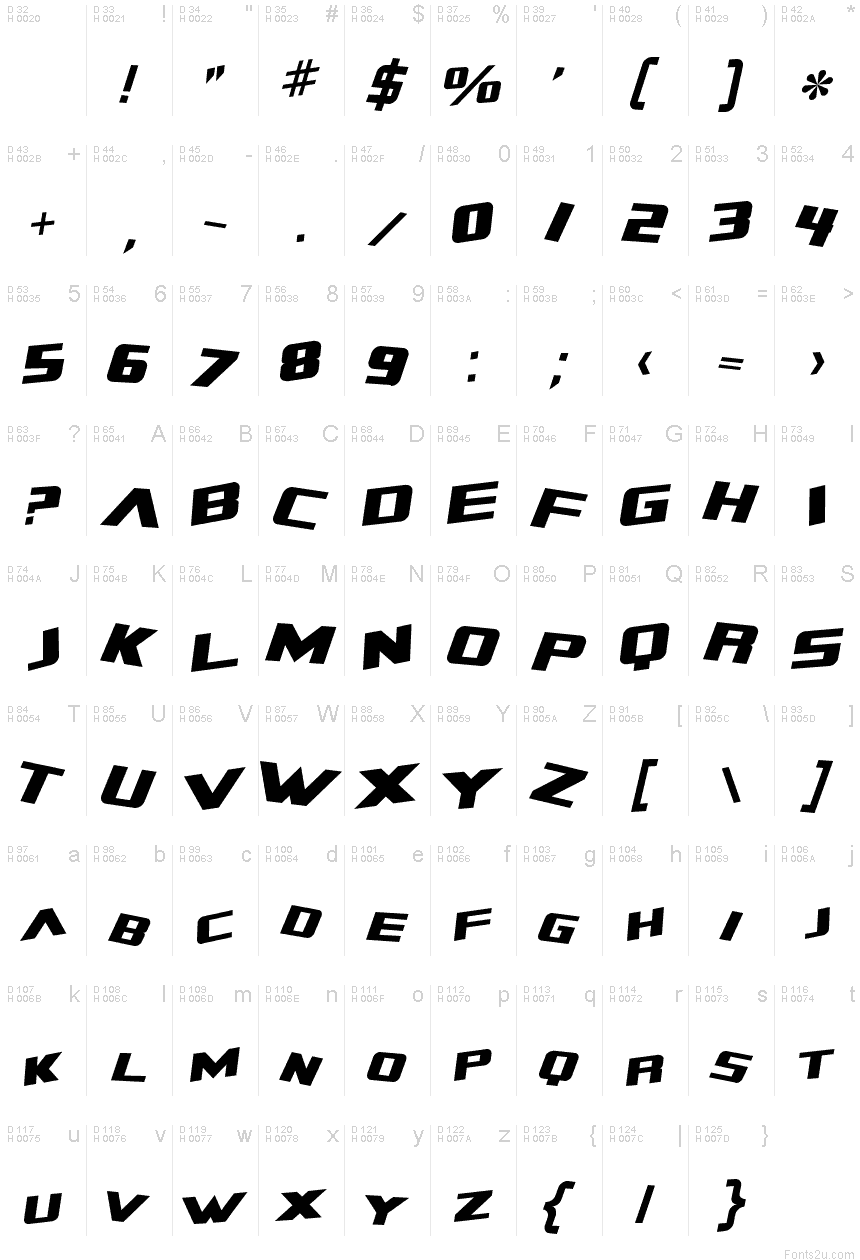
Zero Gravity Extended Italic ist eine kostenlose, futuristische Display-Schrift von ShyWedge aus dem Jahr 1999. Sie versprüht den typischen Sci-Fi-Vibe der späten 90er Jahre mit breiten, nach vorne geneigten Buchstaben und scharfen Winkeln. Die Großbuchstaben wirken gestreckt und aerodynamisch – mit wuchtigen Strichen, gekappten Ecken und einem kompakten, maschinenartigen Rhythmus, der der Schrift ein schnelles, dynamisches Erscheinungsbild verleiht, ohne dabei glattpoliert zu wirken.
Ideal für Postertitel, Gaming-Logos, Club-Flyer, Tech-Events und Magazin-Cover, bei denen das Design von Natur aus Bewegung braucht. Da die Buchstaben breit und aggressiv geneigt sind, eignet sich die Schrift auch hervorragend für kurze Titel oder Monogramme, die einen harten, rasanten Sci-Fi-Look benötigen.